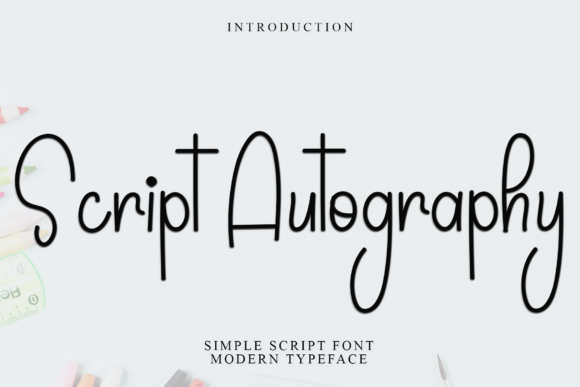
Script Autography
Que vous créiez des produits POD (impression à la demande), des invitations de mariage ou des visuels pour les réseaux sociaux, Script Autography est un choix idéal.